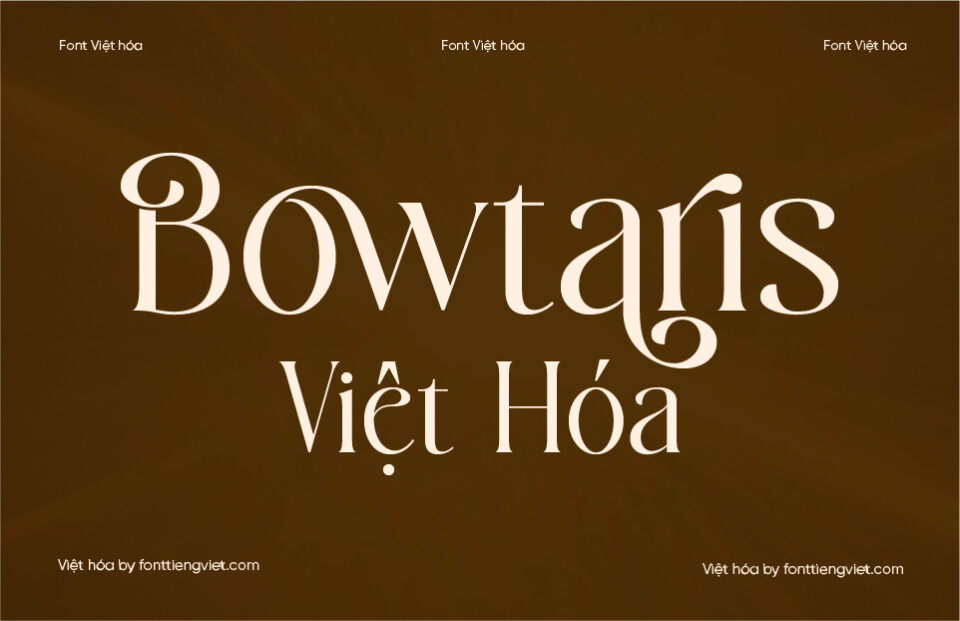
Font Việt hóa 1FTV VIP Bowtaris: Lựa chọn đẳng cấp cho thiết kế đồ họa Việt
Trong thế giới đồ họa hiện đại, việc tìm kiếm một bộ Font Miễn Phí có hỗ trợ tiếng Việt đầy đủ luôn là ưu tiên hàng đầu của các nhà thiết kế. Font Việt hóa 1FTV VIP Bowtaris nổi lên như một hiện tượng nhờ sự kết hợp hoàn hảo giữa nét vẽ cổ điển và hơi thở đương đại. Đây không chỉ là một công cụ gõ văn bản thông thường mà còn là linh hồn của những bản thiết kế cần sự sang trọng, tinh tế và chuyên nghiệp. Với việc tối ưu hóa các dấu câu tiếng Việt theo chuẩn thẩm mỹ, bộ phông này giúp người dùng dễ dàng truyền tải thông điệp một cách ấn tượng nhất trên các nền tảng số và in ấn chuyên dụng hiện nay.
Đặc điểm nổi bật của Font Việt hóa 1FTV VIP Bowtaris trong thiết kế
Phong cách tạo hình độc đáo và tính ứng dụng cao
Font Việt hóa 1FTV VIP Bowtaris sở hữu những đường nét thanh mảnh nhưng vô cùng chắc chắn, tạo cảm giác tin cậy cho người xem. Cấu trúc chữ cái được chăm chút tỉ mỉ với các khoảng hở hợp lý, giúp văn bản duy trì được độ đọc tốt ngay cả ở kích thước nhỏ. Điểm đặc biệt nhất của bộ font này chính là các ký tự thay thế (alternates) và các dấu nối (ligatures) phong phú, cho phép bạn sáng tạo nên những tiêu đề độc bản cho bìa sách, poster phim hoặc bộ nhận diện thương hiệu cao cấp. Khả năng hiển thị sắc nét trên cả màn hình retina và giấy in là một điểm cộng lớn khiến giới mộ điệu luôn săn đón phiên bản này.
Tối ưu hóa tiếng Việt và khả năng tương thích
Sự khác biệt lớn nhất của Font Việt hóa 1FTV VIP Bowtaris so với các phiên bản gốc chính là hệ thống dấu tiếng Việt được thiết kế lại hoàn toàn. Các dấu hỏi, dấu ngã và dấu nặng được đặt ở vị trí cân đối, không làm thay đổi chiều cao của dòng, từ đó tránh hiện tượng chồng chéo ký tự thường gặp. Điều này đặc biệt quan trọng khi thiết kế các layout tạp chí hoặc nội dung website dài. Ngoài ra, phông chữ này tương thích hoàn hảo với các phần mềm đồ họa phổ biến như Adobe Photoshop, Illustrator và Canva, giúp quy trình làm việc của bạn trở nên mượt mà và hiệu quả hơn bao giờ hết.
Cách sử dụng Font Việt hóa 1FTV VIP Bowtaris hiệu quả
Ứng dụng trong truyền thông và quảng cáo
Để phát huy tối đa vẻ đẹp của Font Việt hóa 1FTV VIP Bowtaris, bạn nên sử dụng nó cho các tiêu đề chính hoặc các đoạn trích dẫn quan trọng. Khi kết hợp với các phông chữ không chân (Sans-serif) đơn giản ở phần nội dung, Bowtaris sẽ tạo ra một sự tương phản thị giác đầy lôi cuốn. Đối với các bạn học sinh và sinh viên, đây là lựa chọn tuyệt vời để trang trí bài thuyết trình hoặc làm báo tường điện tử, mang lại cảm giác mới mẻ và hiện đại cho các dự án giáo dục. Đừng ngần ngại thử nghiệm với các hiệu ứng đổ bóng hoặc gradient để làm nổi bật thêm các đường cong mềm mại của bộ font đặc sắc này.